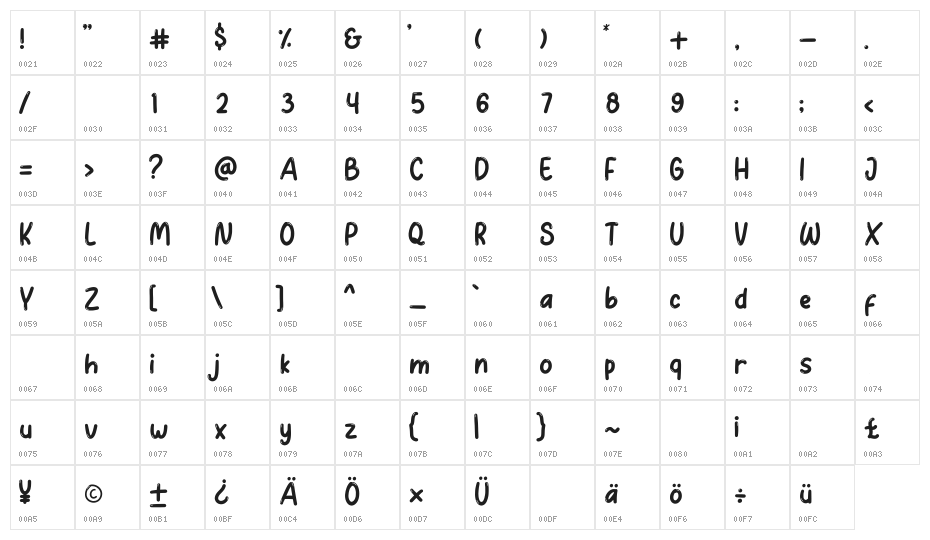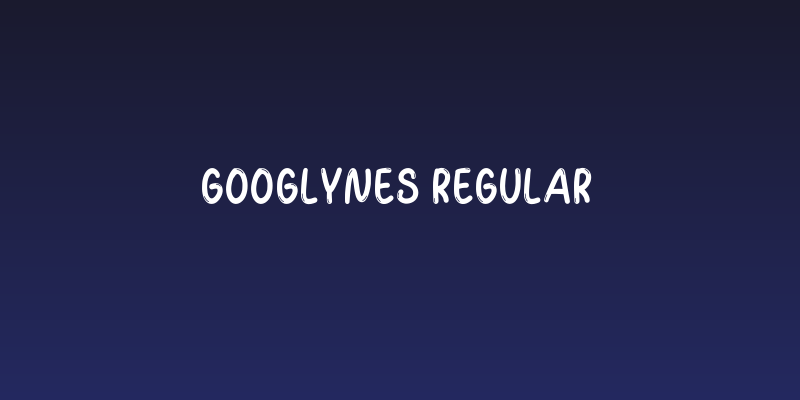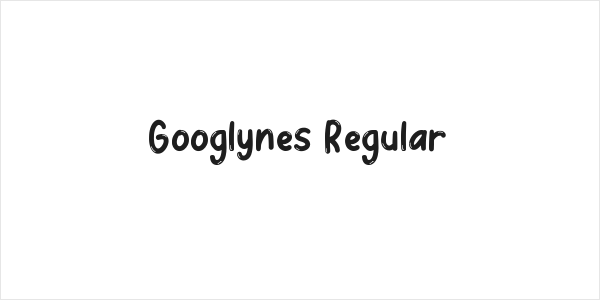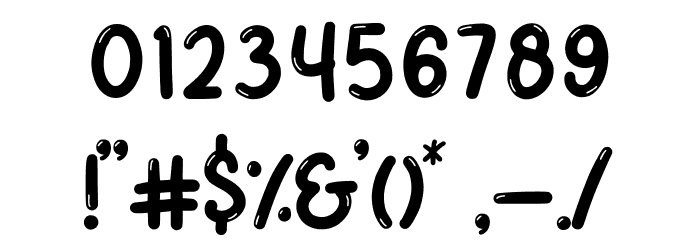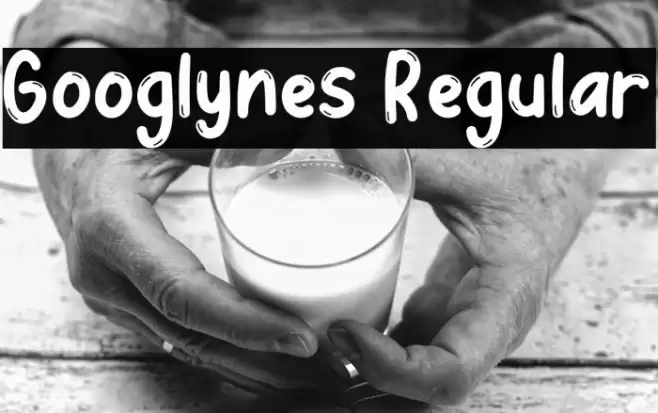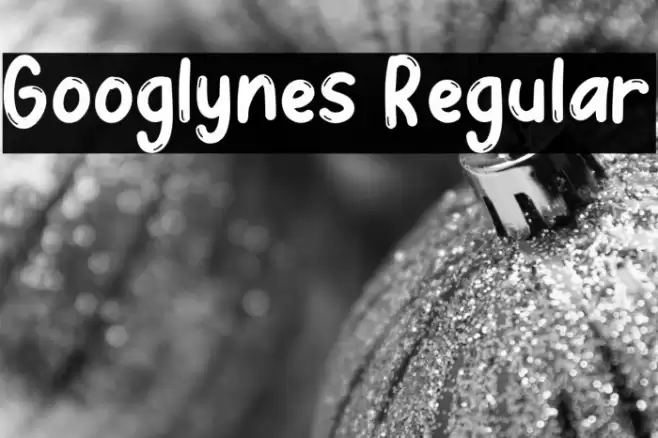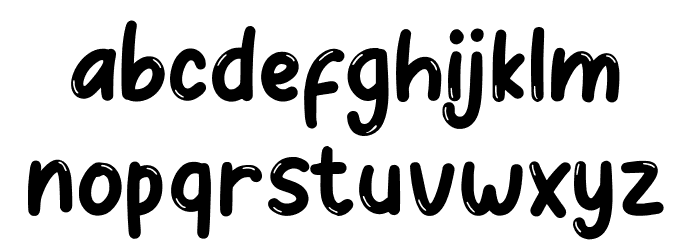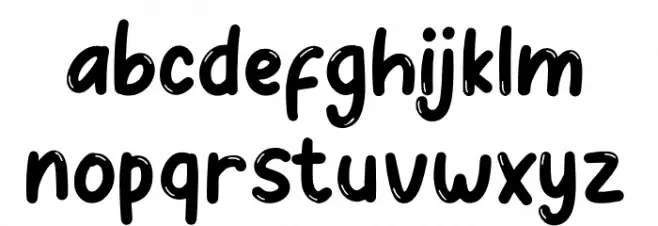
Googlynes Regular Font
✎ Cartoon
| Категория | Cartoon |
| Общий стиль | Playful, Whimsical |
| Рекомендуемые проекты | Ideal for children's books, playful branding, casual invitations, and creative posters. |